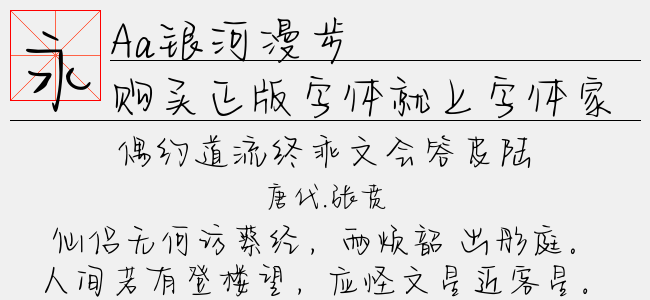
Aa银河漫步 字体大小5.16 M,包含了6763个汉字以及附加其他英文字体和阿拉伯数字,属于Aa字体。Aa银河漫步(TTF)可以免费下载,商业用途请自行购买版权,它的特征就是手写,手书风格,行书,钢笔,采用安装嵌入的安装方式,支持符号拉丁文日文中文等语言
字体作者:Aa字体
字体名称:Aa银河漫步